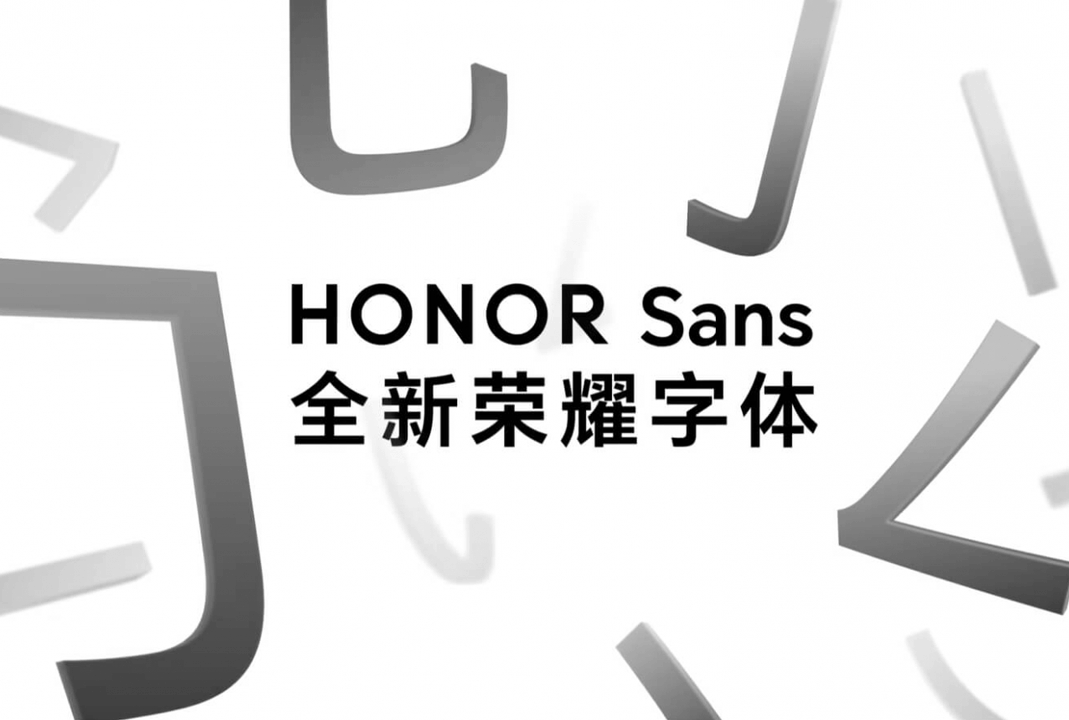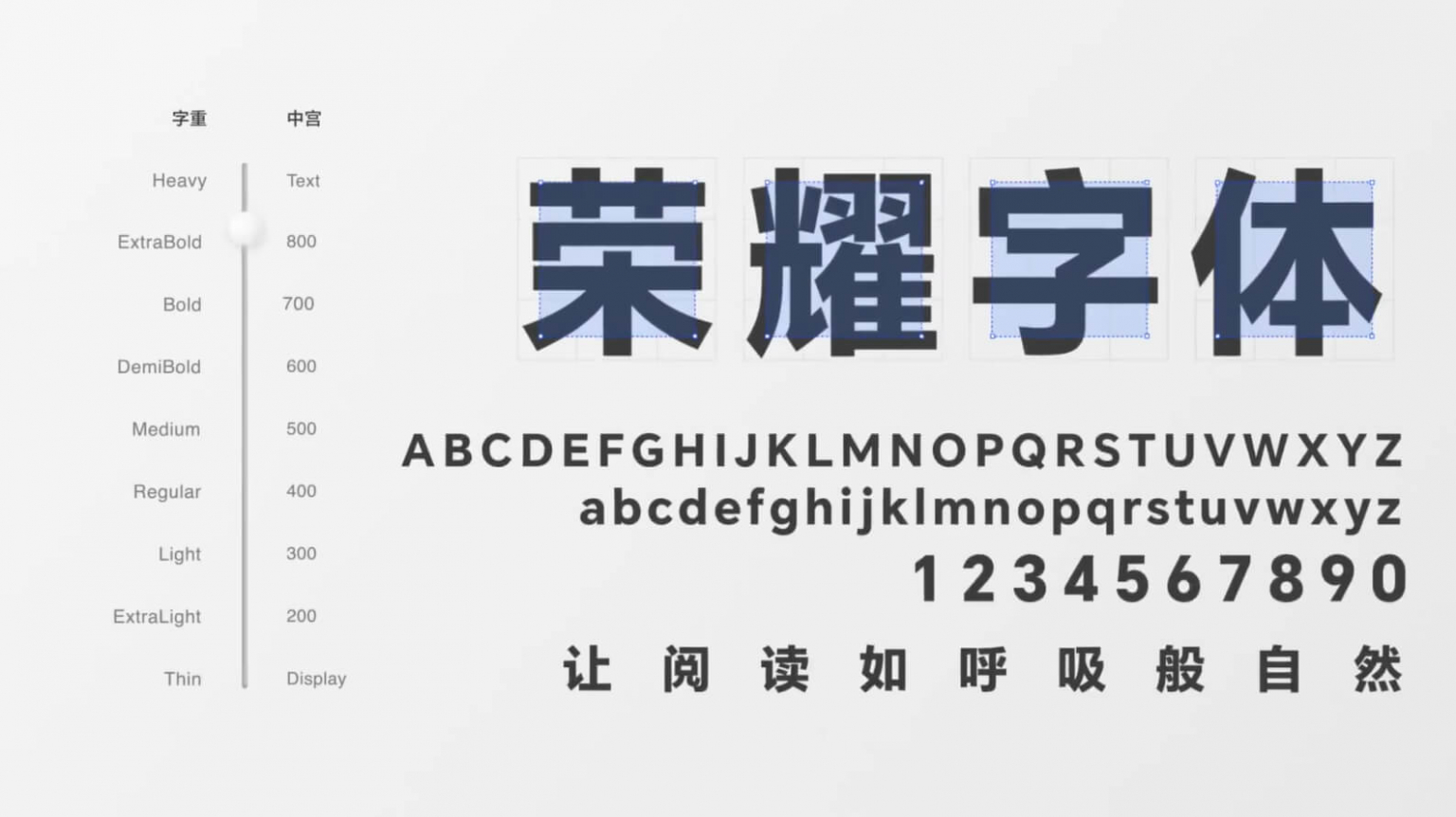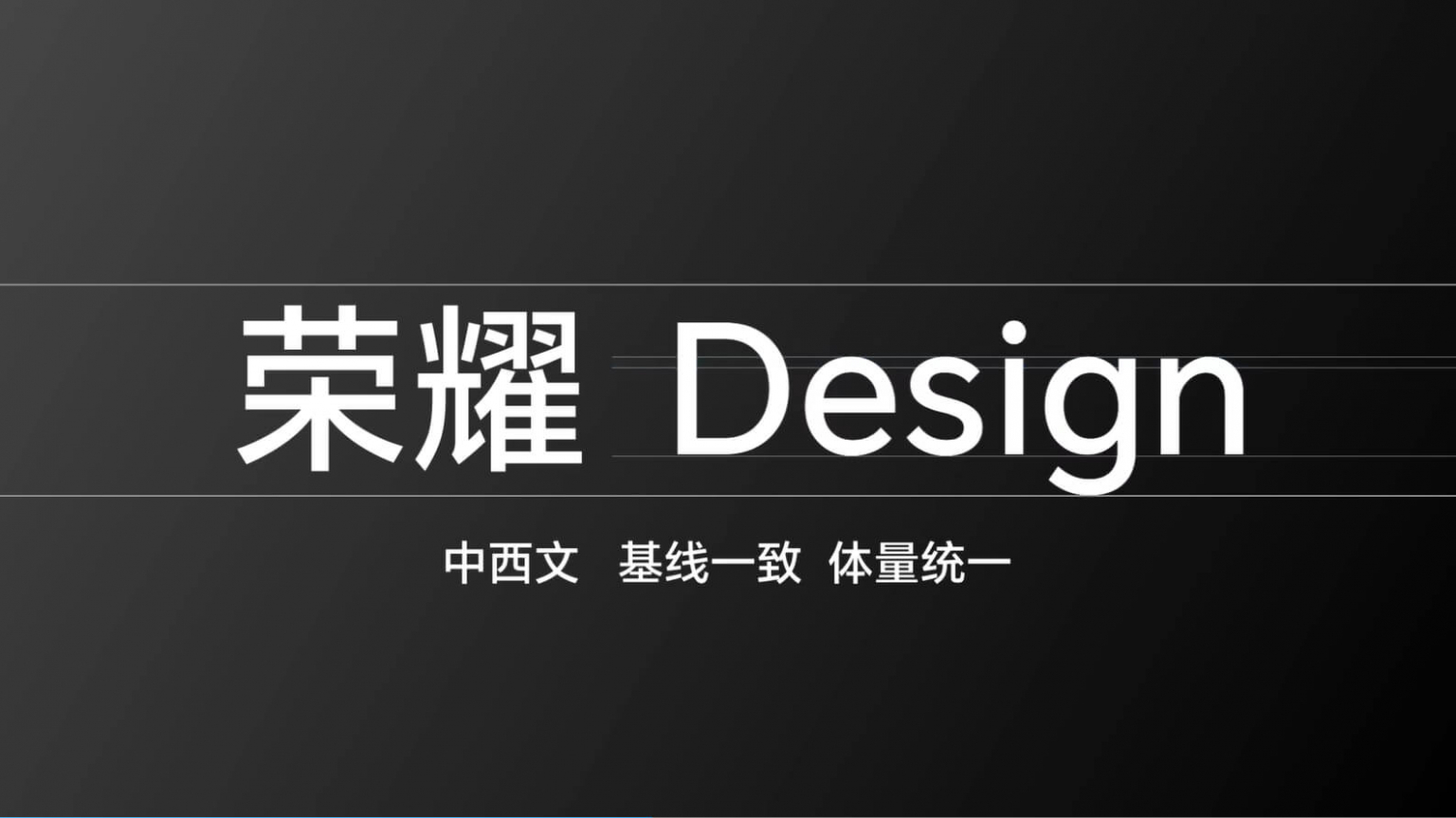
荣耀 HONOR Sans 字体,荣耀将其称为“会呼吸的字体”。HONOR Sans 将面向全社会免费授权开放,覆盖全场景全人群使用,而且未来也将推送到荣耀全场景设备上。
荣耀 MagicOS 7.0 发布会上带来了全新的 HONOR Sans 字体,宣称是业界首款支持字重和中宫双重无极可变的字体,将荣耀字体与 UI 融合,通过间距优化,让排版更整齐,层次更清晰。